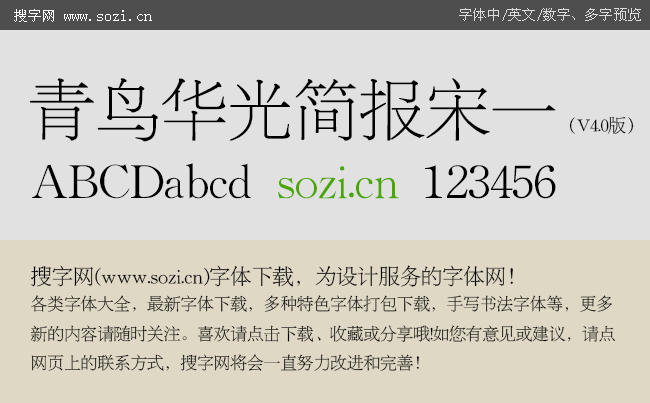
青鳥(niǎo)華光簡(jiǎn)報(bào)宋一
搜字網(wǎng)提供一款青鳥(niǎo)華光簡(jiǎn)報(bào)宋一中文字體下載,青鳥(niǎo)華光簡(jiǎn)書(shū)宋一字體是青鳥(niǎo)華光字庫(kù)中的一種字體,字形清秀美觀,筆畫(huà)清晰,中正大氣,一筆一畫(huà),清晰明了。本作品適用于書(shū)籍排版、報(bào)紙排版、畫(huà)冊(cè)設(shè)計(jì),網(wǎng)頁(yè)設(shè)計(jì)等應(yīng)用。